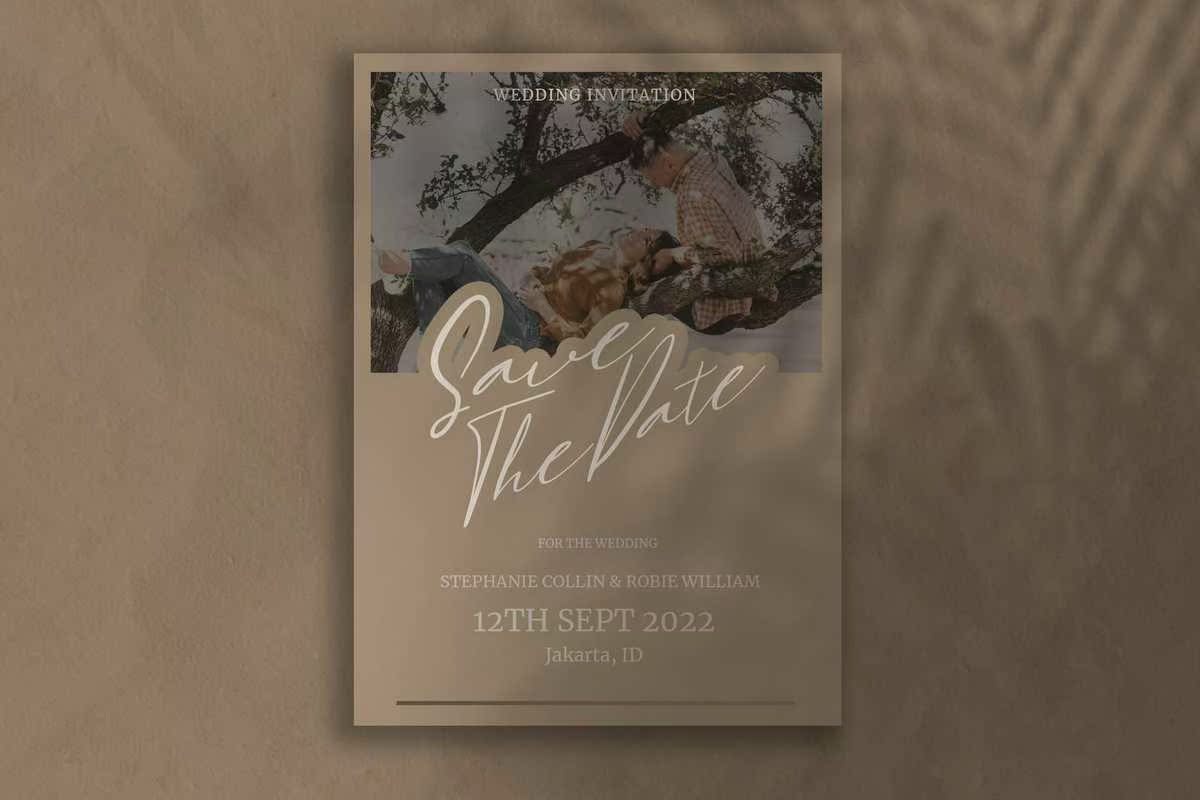
汉堡签名是一种样式化的签名,描述了它看起来非常优雅和优雅。这种东西和精致的外观是由不同的设计理念组成的。汉堡签名是经过编码的,您可以使用这些符号和Swashease!汉堡签名是一种样式化的签名,描述了它看起来非常优雅和优雅。这种东西和精致的外观是由不同的设计理念组成的。汉堡签名是经过编码的,您可以使用这些符号和Swashease!